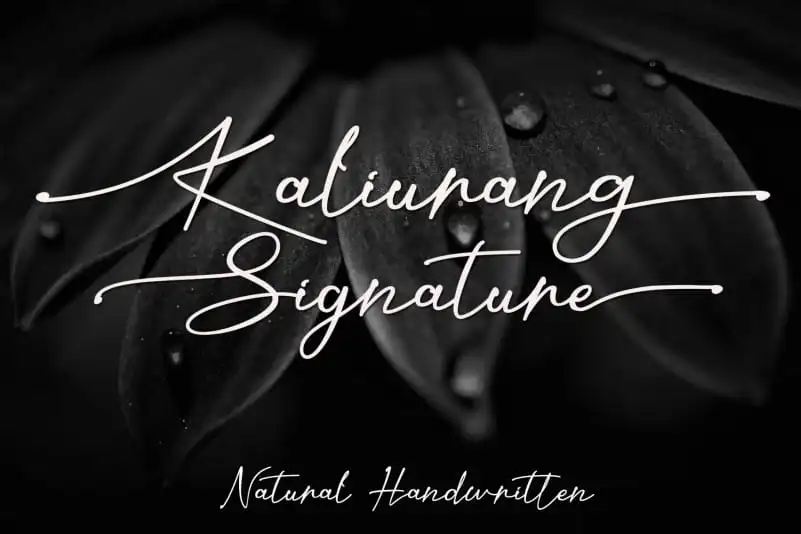
Kaliurang Signature Font – Fonte Grátis
Kaliurang Signature Font
Kaliurang Signature Font é uma linda fonte escrita a mão que adicionará um toque moderno e elegante às suas designs tipográficas. Criada pela Letterafa Studio, esta fonte escrita a mão tem letras onduladas e suaves que conferem um aspecto único e delicado aos seus projetos. Kaliurang Signature é perfeito para uma ampla variedade de usos, como logomarcas, cartões de felicitações, design de embalagens, identidade de marca, trabalhos DIY, títulos de livros, convites de casamento e embalagens. Seja qual seja o seu projeto visual, Kaliurang Signature vai trazer uma sensação agradável e única ao seu trabalho. E como sua designer Hamilton nos apresenta esta fonte, ele mantém um toque pessoado e encantador que fará seu design se destacar ainda mais. Esta fonte escrita a mão em estilo moderno tem letras fluidas com movimentos suaves e finos, ideal para criar designs distintivos e acolhedores. Kaliurang Signature é uma escolha ótima para qualquer designer gráfico ou freelancer que busca um touch pessoal e sofisticado no seu trabalho visual. Seja você um criador de logomarcas, um designer de embalagens ou um profissional de marketing digital, esta fonte escrita a mão está aqui para ajudar a tornar seus designs mais atraentes e únicos. Além disso, sua elegância moderna faz dela uma escolha excelente tanto para uso pessoal quanto em projetos profissionais.